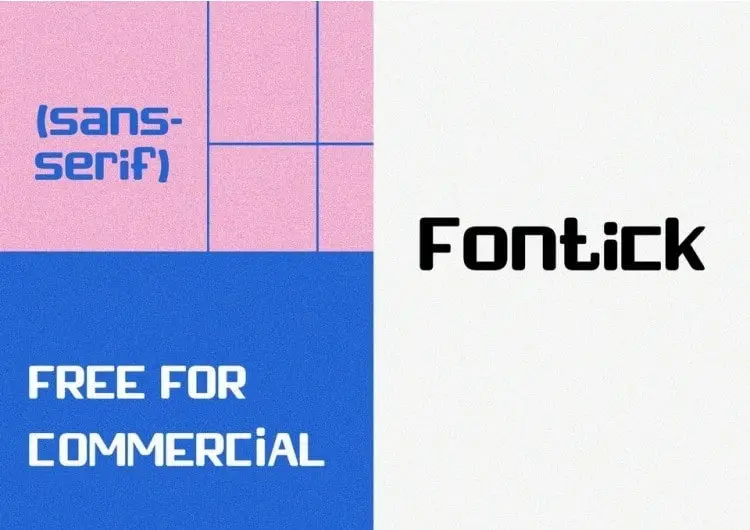
Fontick Sans Serif é uma elegante escolha para qualquer projeto que valorize conforto visual e facilidade de legibilidade. Com terminais levemente arredondados, esta fonte traz uma sensação amigável e suave ao seu design, ideal para ambientes digitais como sites, aplicativos ou editoriais online. Cada detalhe foi cuidadosamente pensado por Maxim Raikov para proporcionar um apelo atraente, combinando elementos de simplicidade do sans serif com uma conotação quente e divertida. Multilíngue, incluindo suporte para inglês e russo, Fontick é perfeito tanto para o texto de corpo quanto para headlines em tamanhos maiores. Seja você um designer ou desenvolvedor de sites, está sempre a procura de uma fonte que combine elegância com utilidade, Fontick Sans Serif é a escolha ideal para criar um design visual envolvente e atraente.